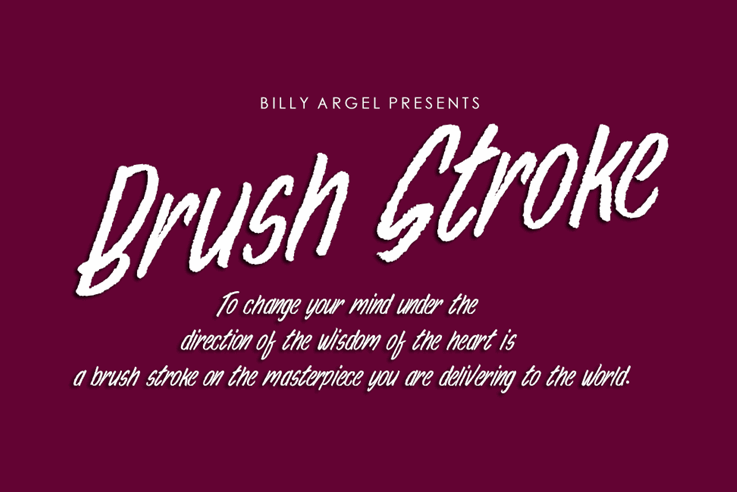
Brush Stroke Font
A fonte “Brush Stroke Font” é uma criação elegante e versátil do designer Billy Argel, perfeita para quem busca expressar seu estilo através de letras suaves e detalhadas. Esta categoria de fontes script oferece um gráfico fluido que transmite calma e sofisticação, ideal tanto para escrita personalizada quanto para aplicação comercial. Billy Argel destaca-se com sua habilidade em transformar linhas leves em arte vibrante, criando uma linguagem única que se ajusta perfeitamente à ideia de Brush Stroke Font. Se você está procurando por um recurso gráfico que seja tanto versátil quanto sofisticado, esta fonte é uma escolha impecável para seus projetos. Independentemente do seu propósito – seja para criar conteúdo pessoal ou material comercial – essa fonte irá transformar suas ideias em texturas perfeitas e detalhes vibrantes. Se você deseja explorar ainda mais as capacidades de Billy Argel, visite o site oficial: www.billyargel.com. Aqui, você encontrará tudo sobre a fonte Brush Stroke Font e outras incríveis criações do designer.